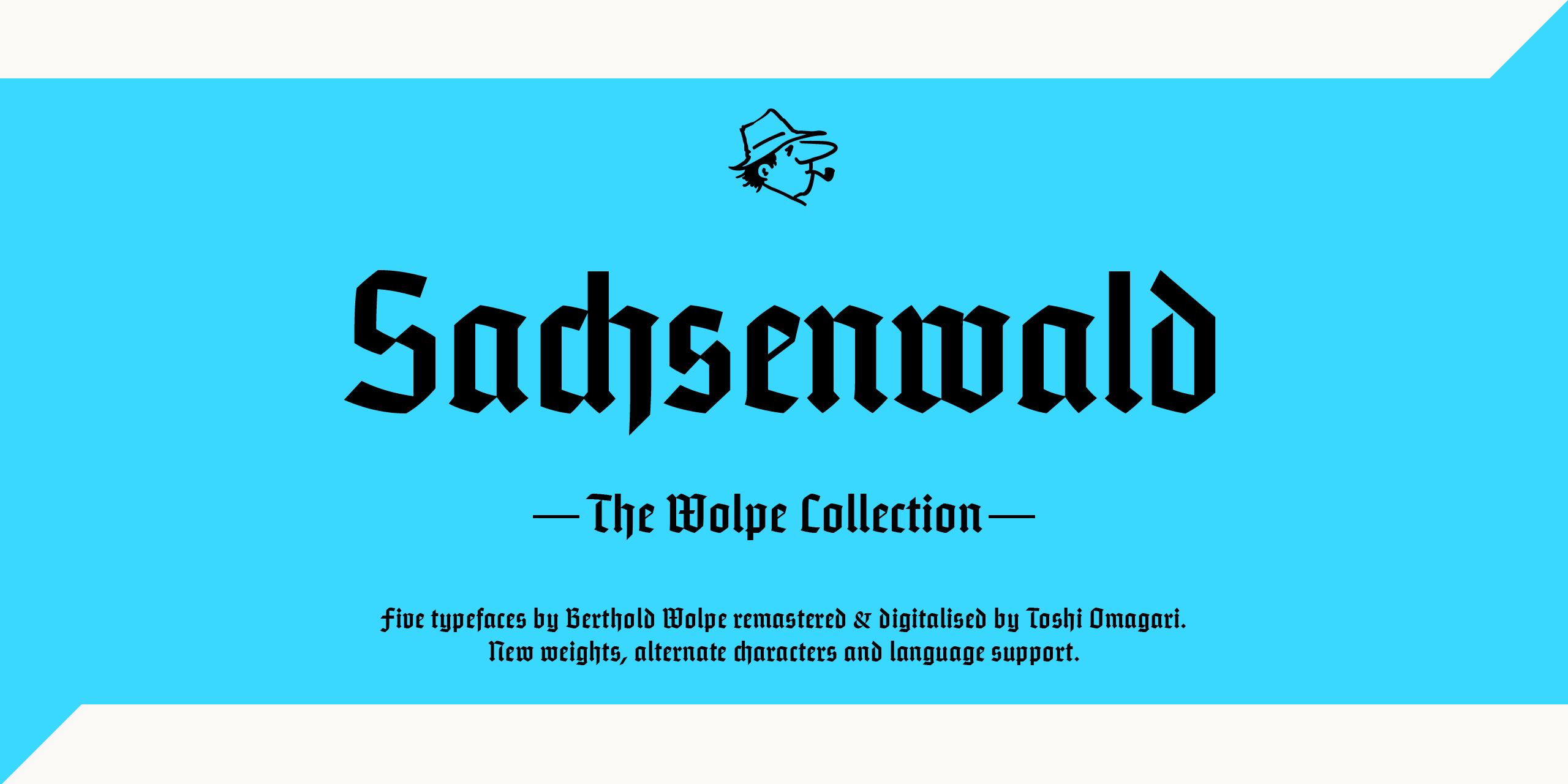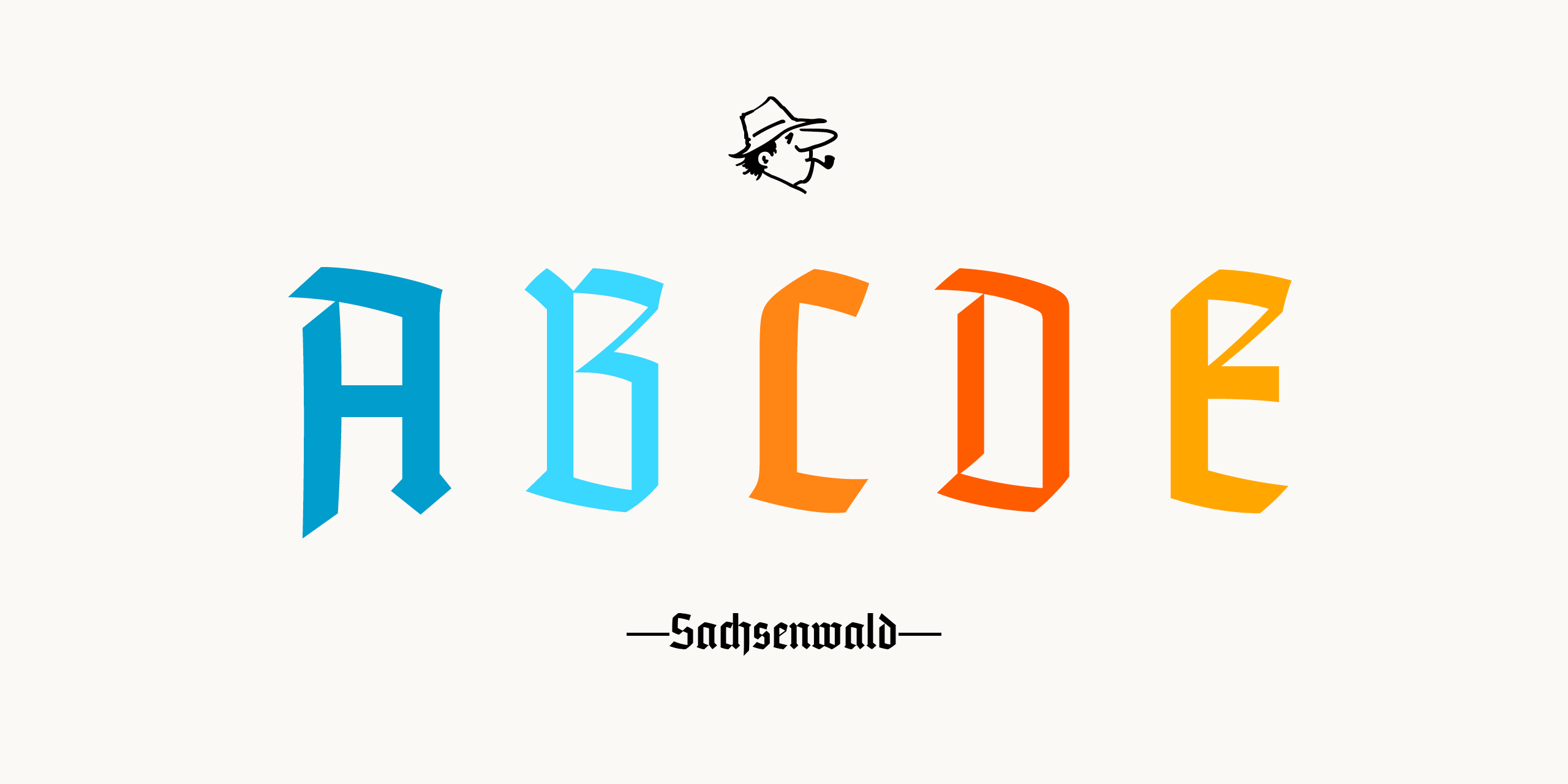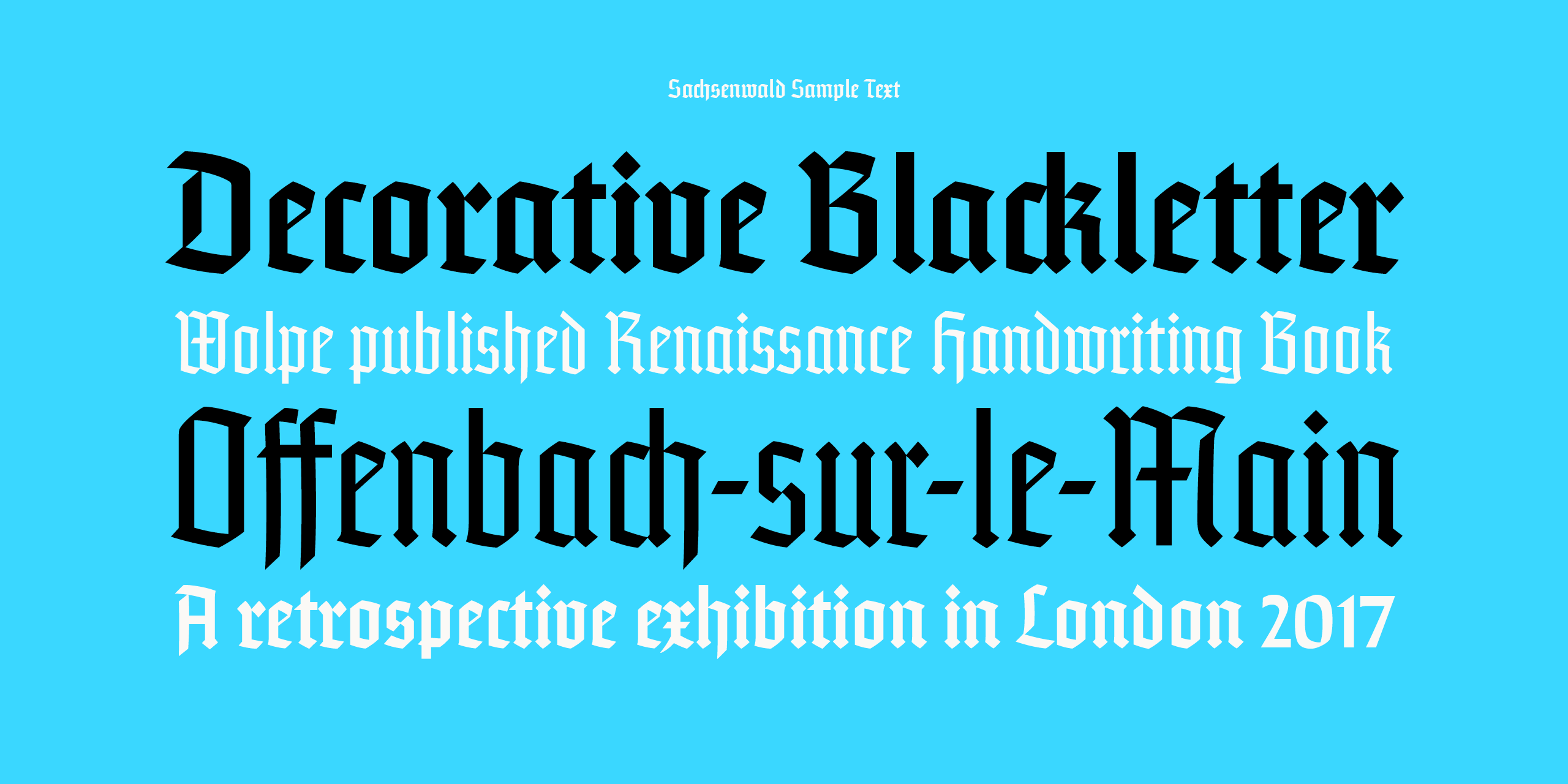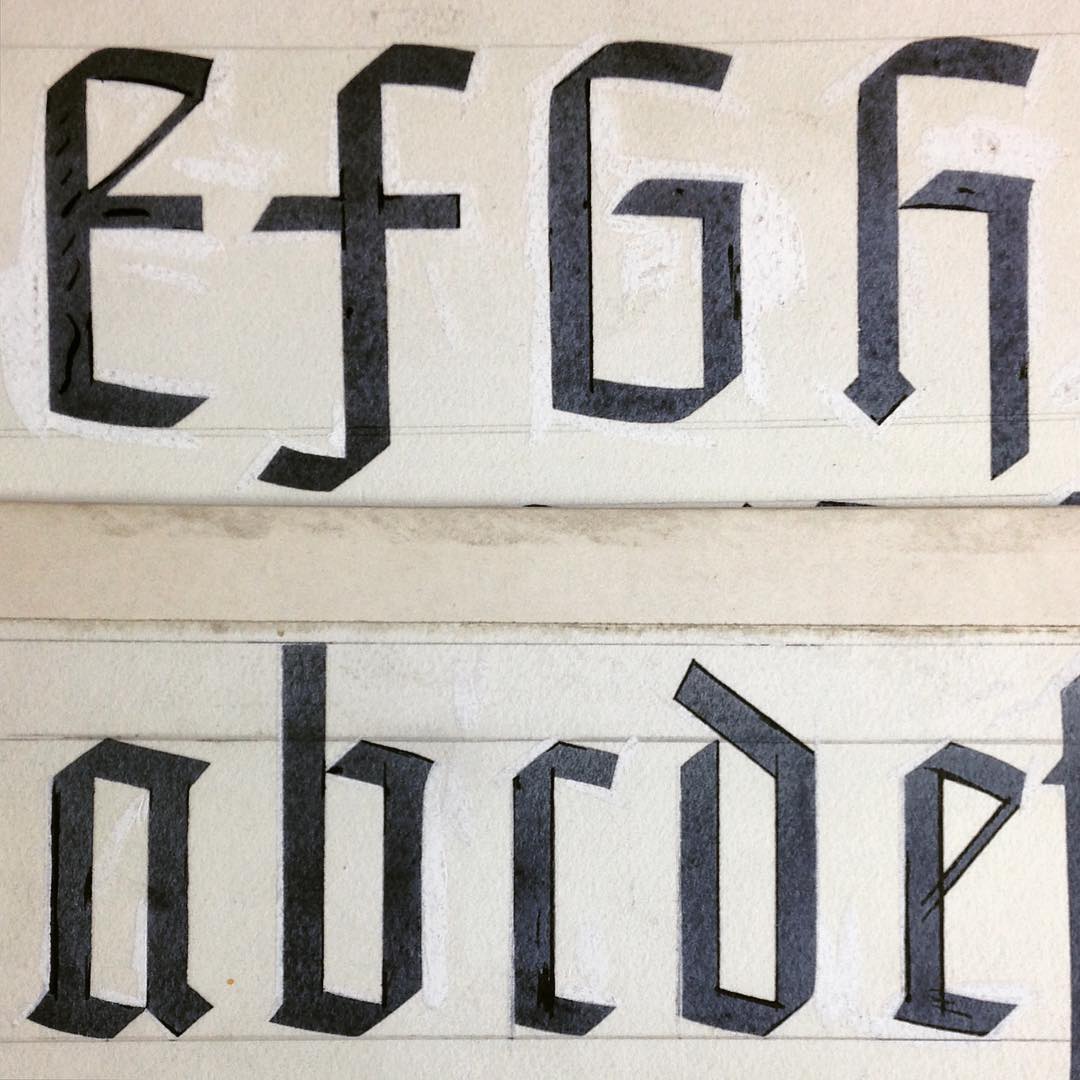
- 1936
- Gebrochene Schrift
Berthold Wolpe musste wegen seiner jüdischen Wurzeln in den 1930er-Jahren nach England fliehen und fand dabei in Stanley Morison einen Unterstützer. In den Unterlagen im Monotype-Archiv taucht Wolpes Sachsenwald-Entwurf 1936 zunächst als »Bismarck Schrift« auf. Die Dokumente weisen auch den deutschen Ullstein-Verlag als einen Auftraggeber der ersten Schnitte aus. Neben Deutschland, wo die schlichten Gotischen gerade im Trend lagen, visierte man aber auch den englischen Markt an und überarbeitete die Zeichen – und letztlich auch den Namen – entsprechend. Die Feinarbeit am Entwurf wurde in den ausgehenden 1930er-Jahren fortgesetzt, aber mit dem 2. Weltkrieg und der Abschaffung der gebrochenen Schriften als Verkehrsschrift im Deutschland (1941) waren die Bedingungen für den Vertrieb der Schrift nicht mehr gegeben und sie geriet auch bei Monotype in Vergessenheit.
Eine Digitalisierung in einem Schnitt wurde von Gerhard Helzel angefertigt. Monotype hat die Sachsenwald 2017 als Teil einer Wolpe-Kollektion in zwei Schnitten neu aufgelegt.